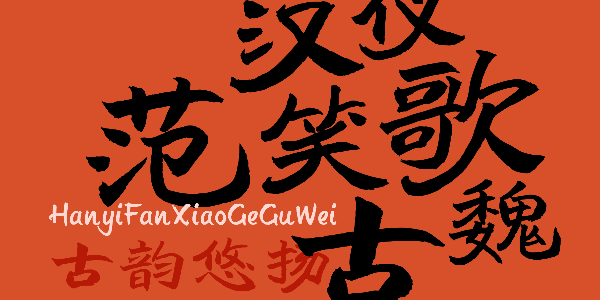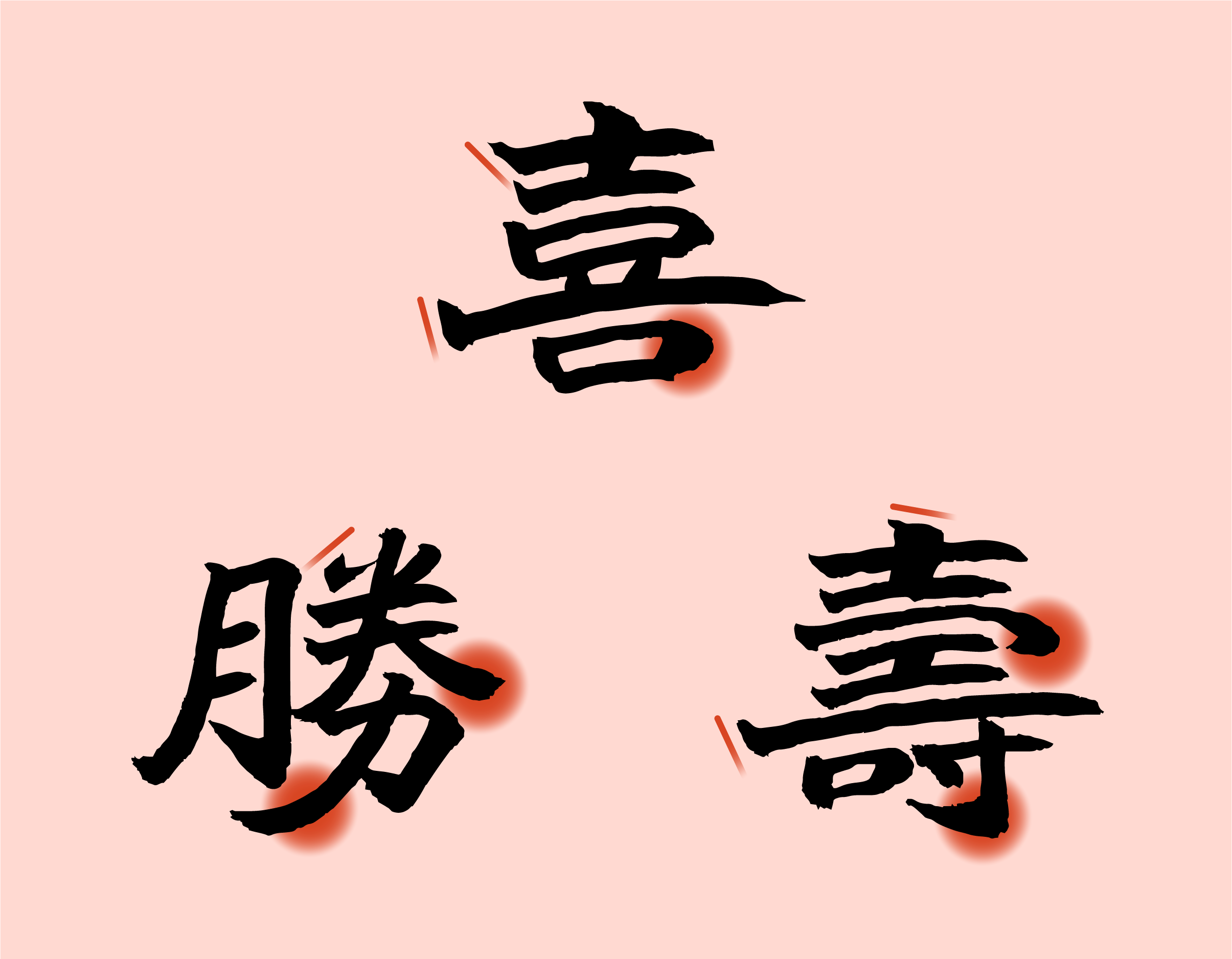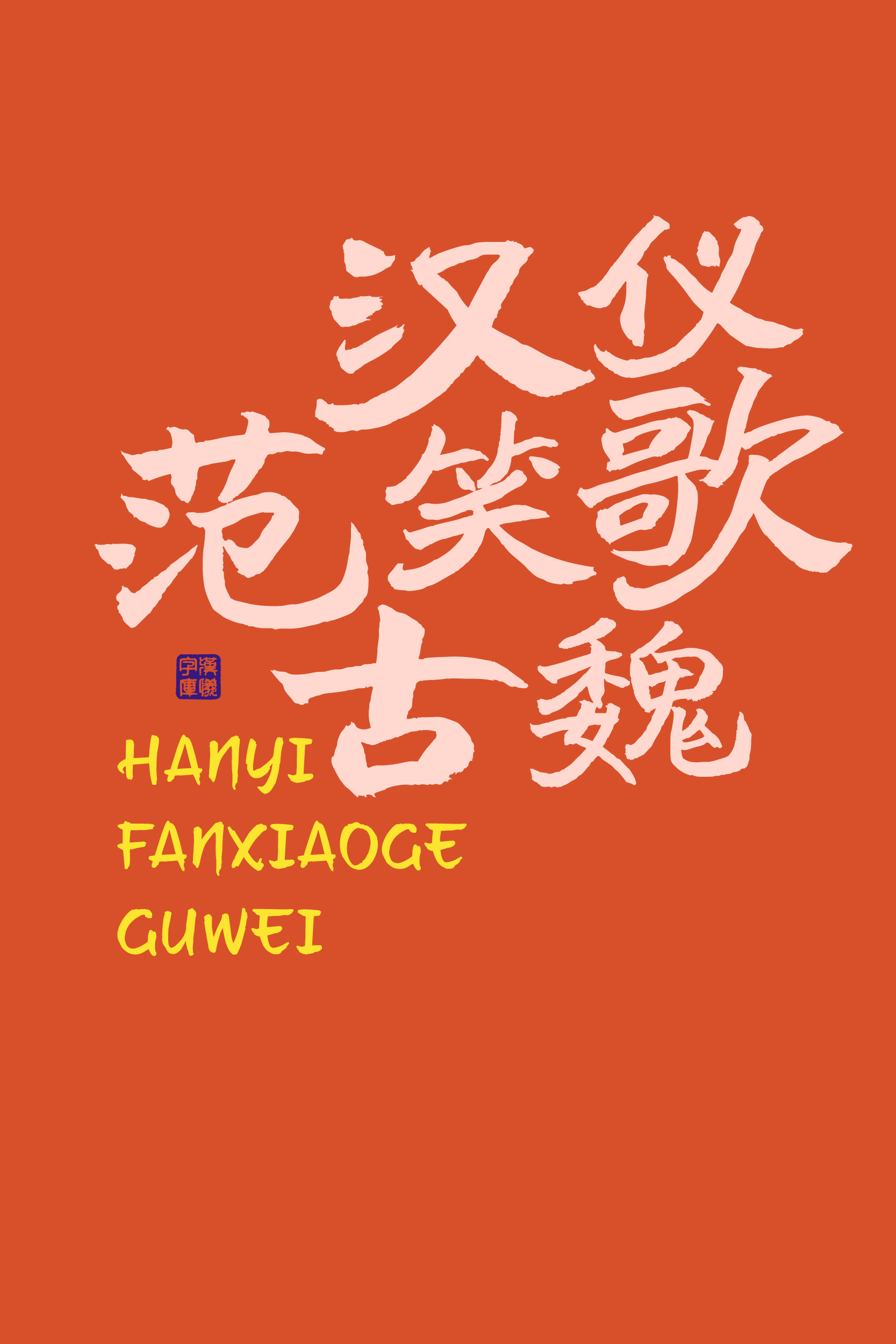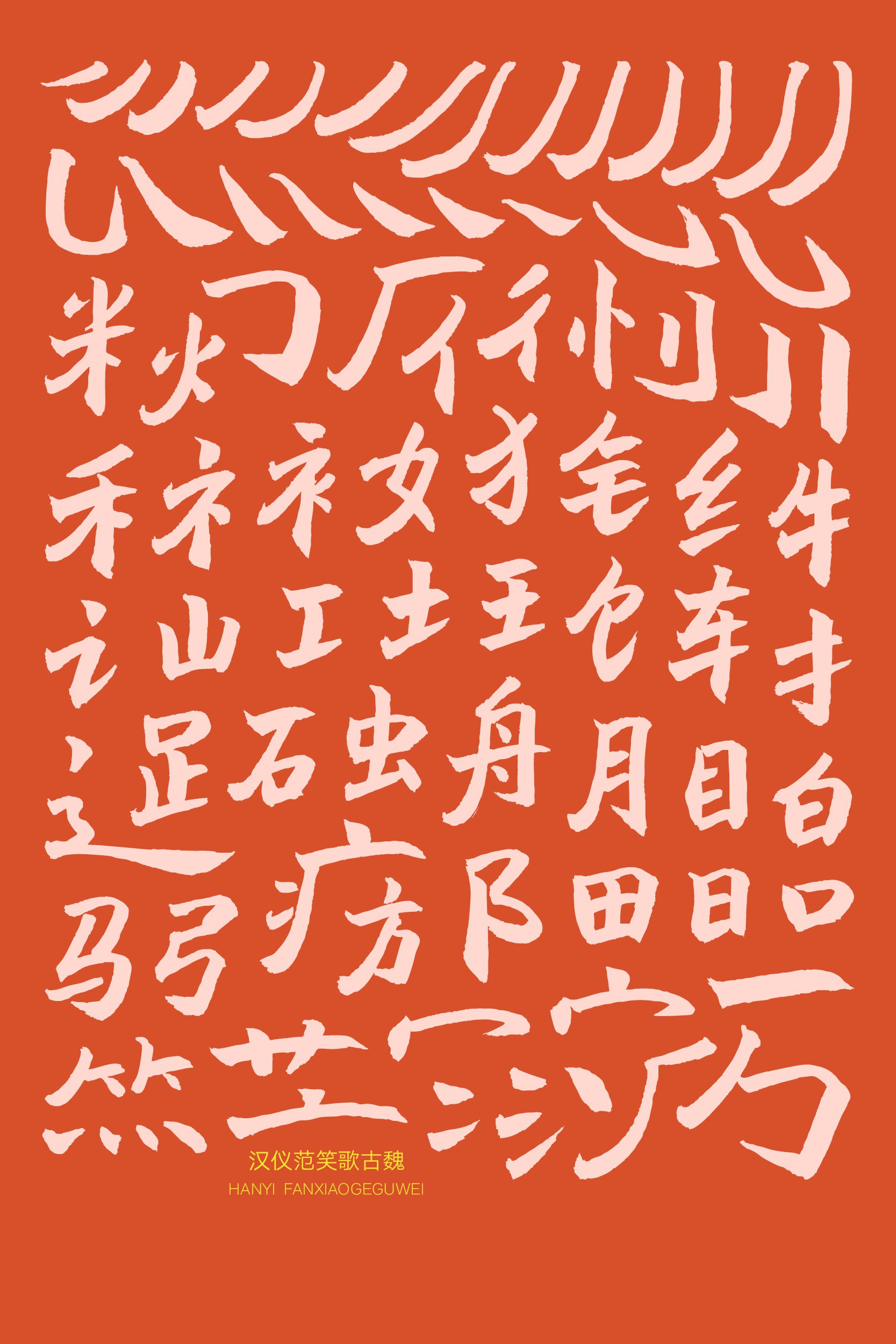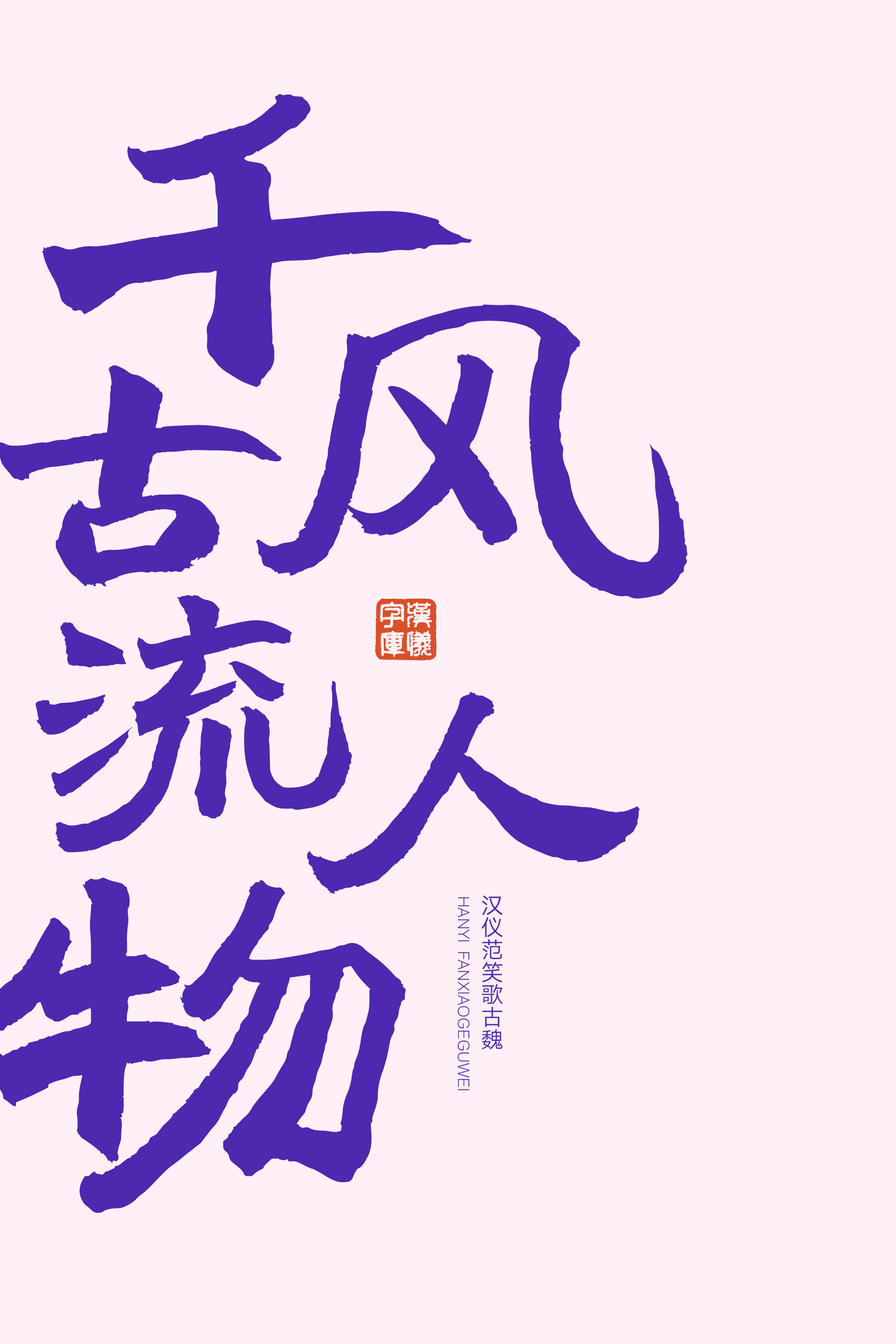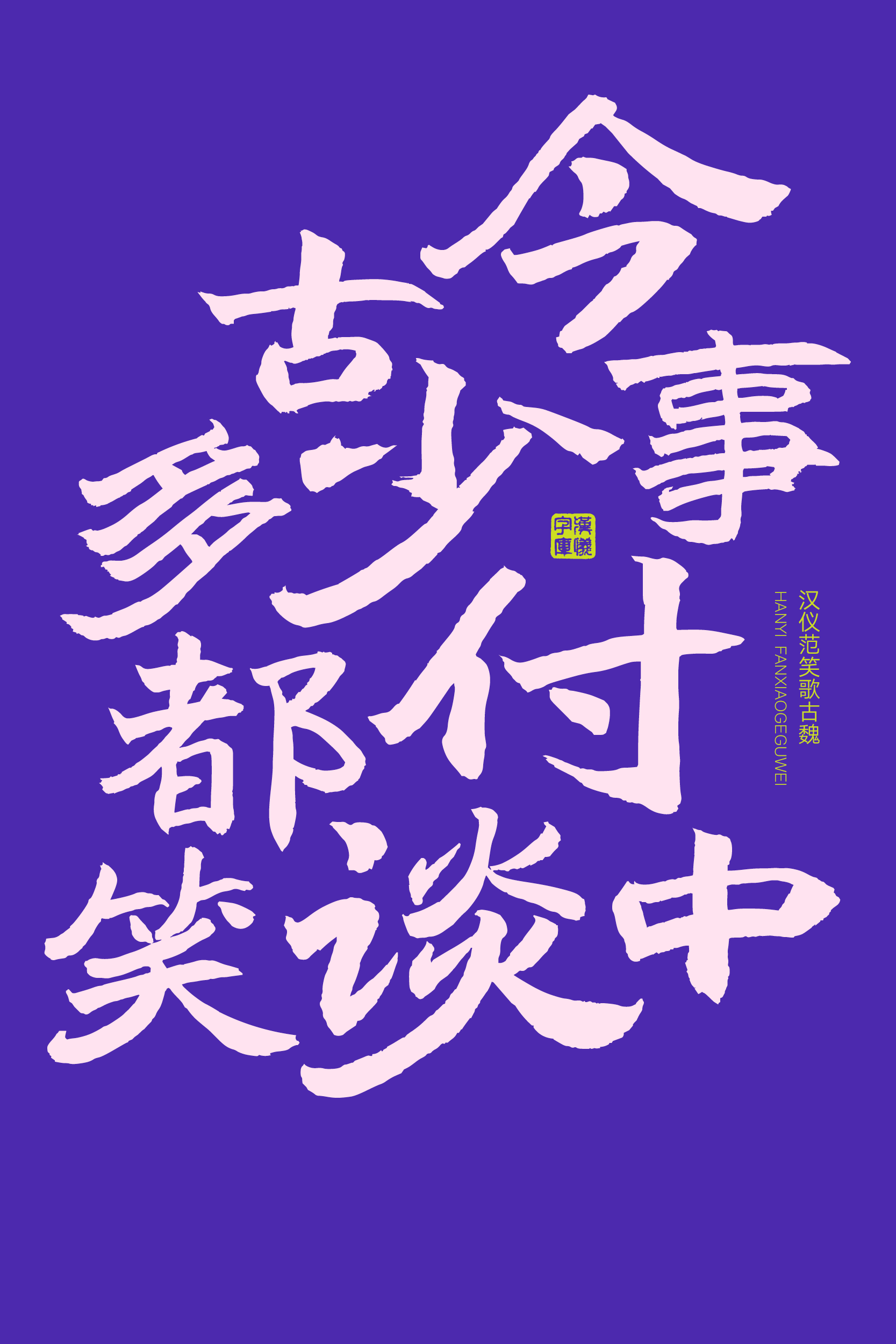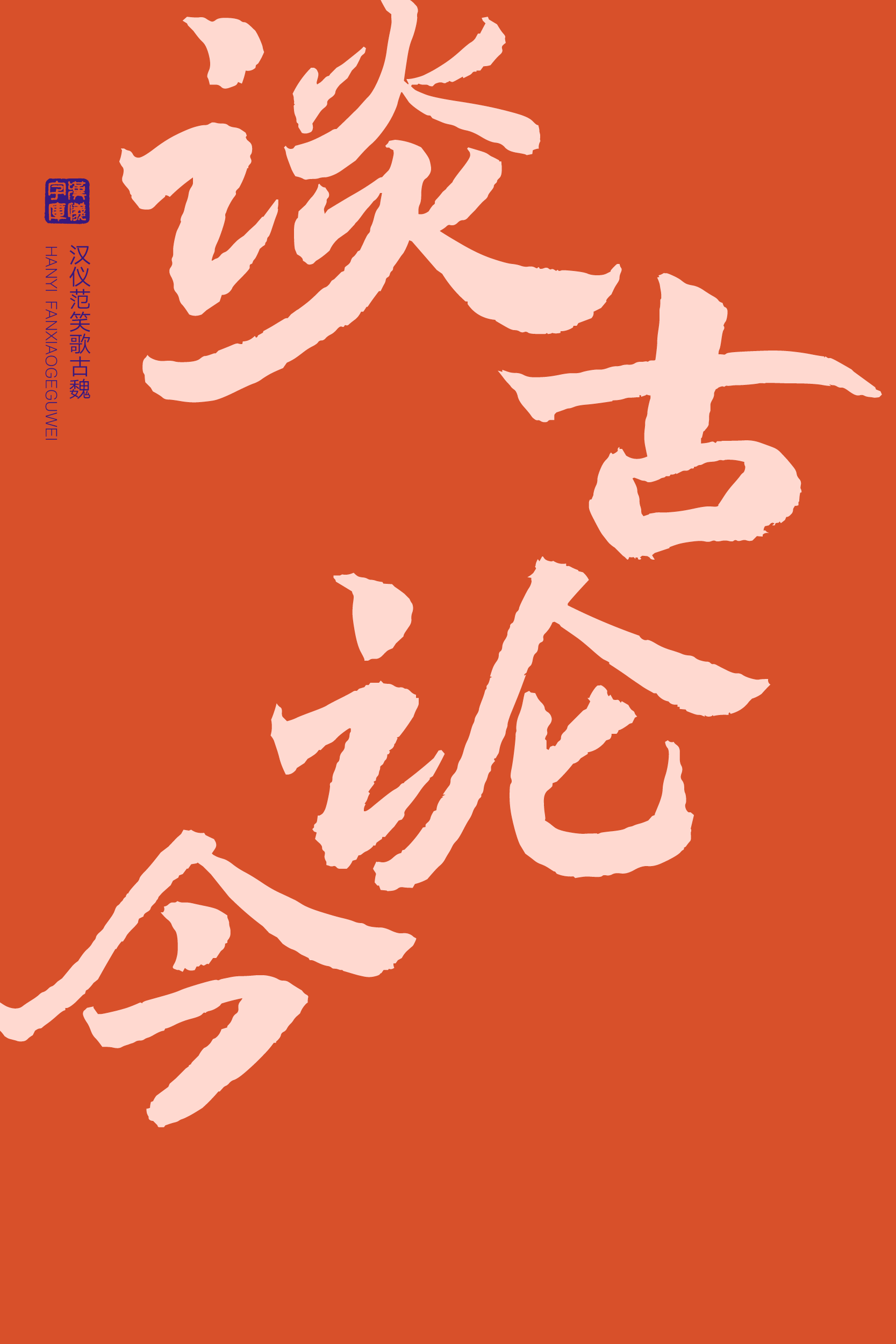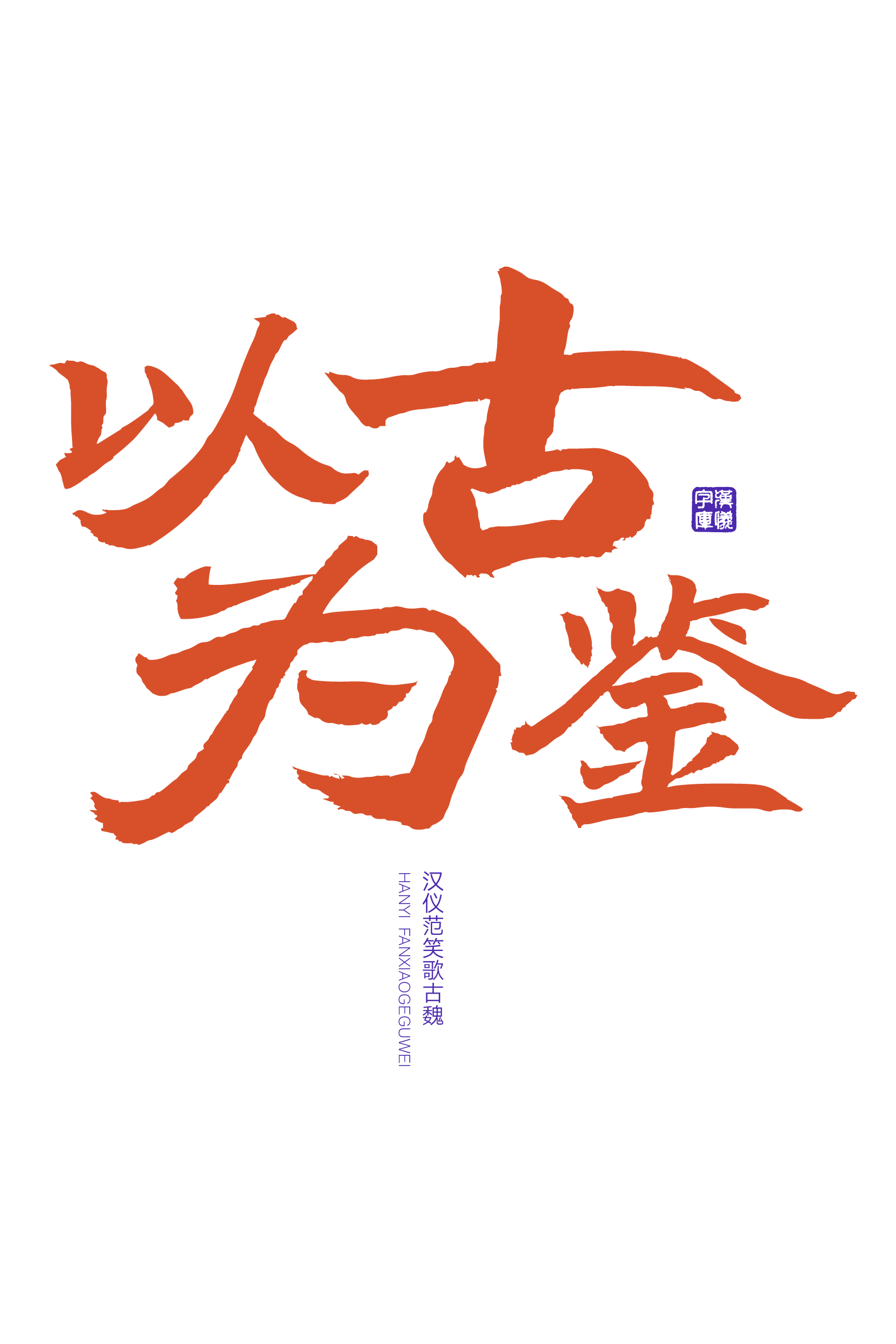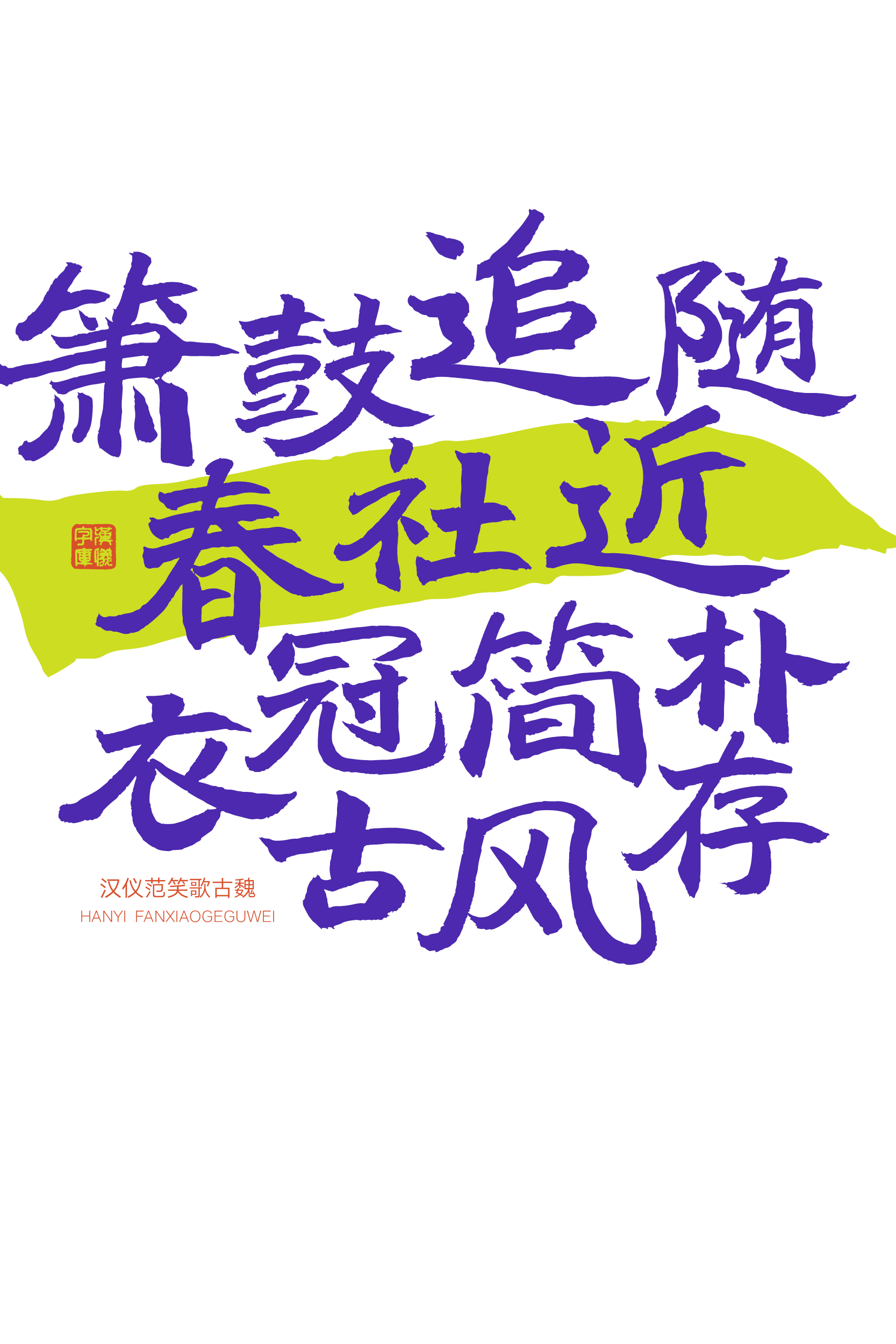
汉仪范笑歌古魏
古韵悠扬,风度翩翩,汉仪范笑歌古魏是一款秀美潇洒的魏楷风格书法字体,汲取清代书家赵之谦作品的精华,造型扁宽、结体疏宕,楷中带隶,呈左低右高倾斜之势,向左右两侧舒展。用笔不完全着意于描摹魏碑笔画的刀刻感,而是在方笔中融入少许浑厚的圆笔,形成独特的书风。这款字体适合作为标题字体应用于文化休闲的广告招牌、包装等场景。
造型扁宽、结体疏宕。
楷中带隶,呈左低右高倾斜之势,向左右两侧舒展。
用笔不完全着意于描摹魏碑笔画的刀刻感,而是在方笔中融入少许浑厚的圆笔。
主笔画突出,内部结构相互揖让、错落有致,长撇长勾从中穿插而过,向左侧伸展,整体更具张力。